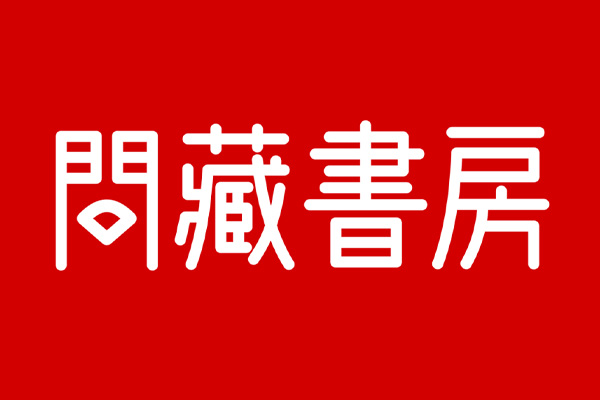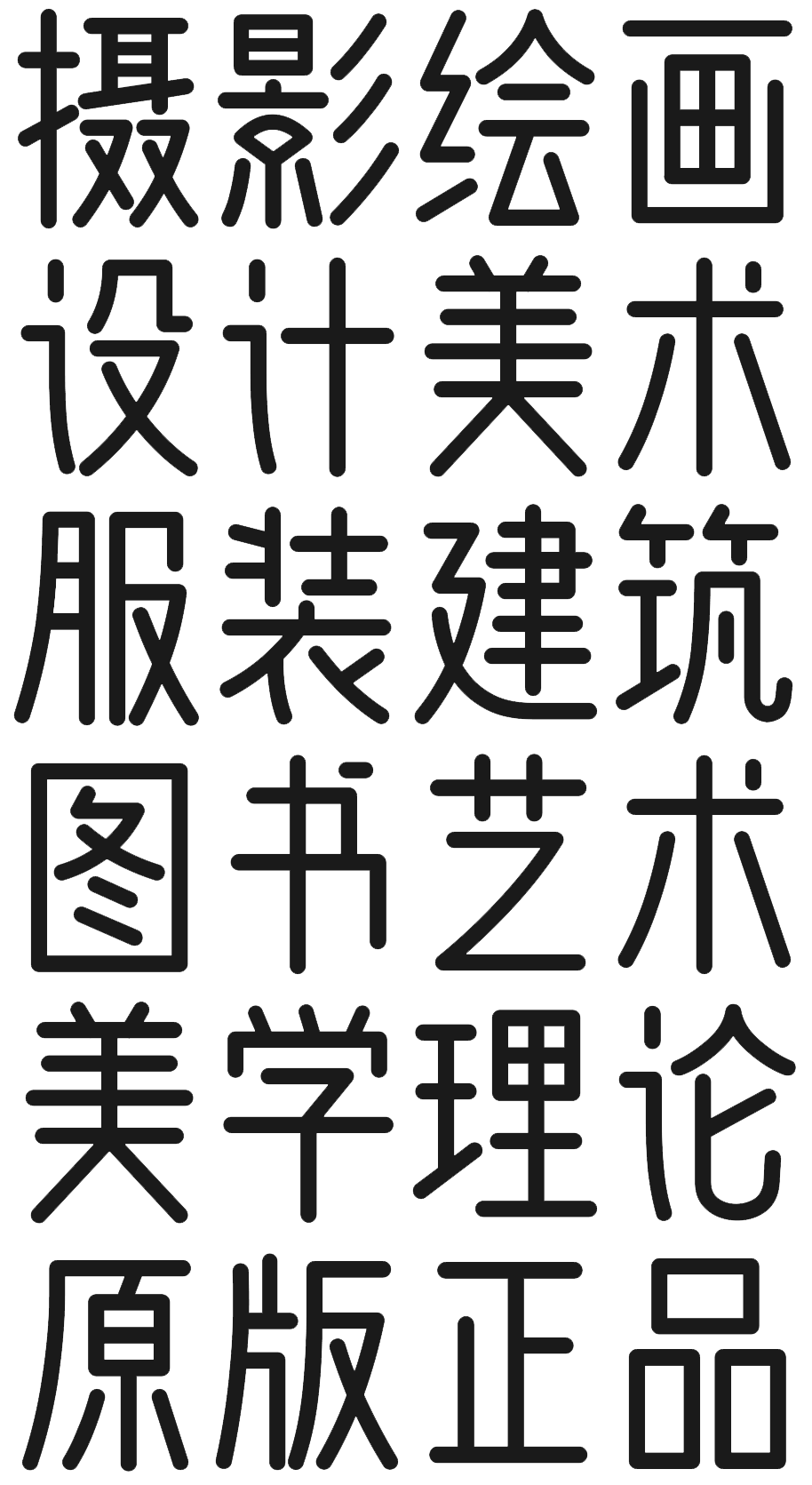
问藏书房
问藏书房与造字工房携手,以始终坚持原创的原则,精心打造了一款名为“问藏书房”的字体。在此建国七十周年之际,决定向大陆地区的所有个人与商业机构免费开放这款字体,以表达对国家所给予的权益政策的感激之情,并回馈一直支持我们的正版字体客户和朋友!
问藏书房字体的设计风格现代简约,紧凑的中宫带来极富层次的视觉阅读体验。每个字形都俊秀优雅,且呈现出一种古朴典雅的风格。设计团队精心打造了这款字体,赋予了汉字全新的美感!
问藏书房效果预览
问藏书房字体效果预览